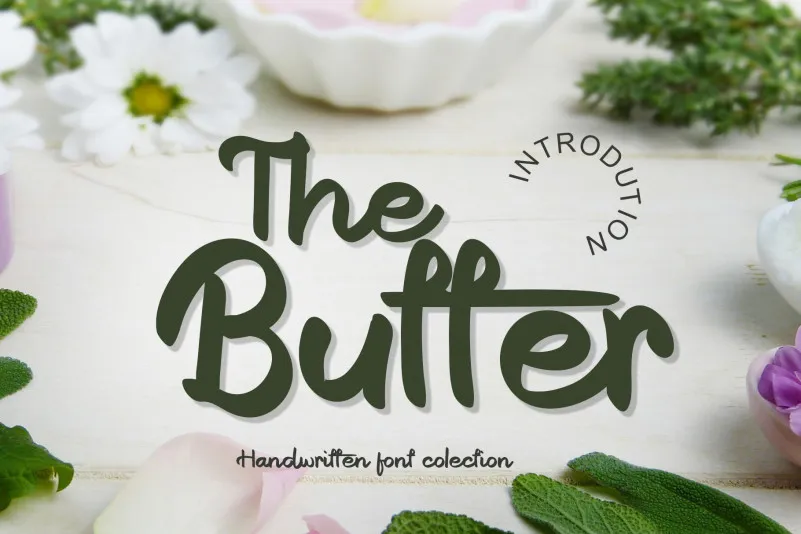
The Butter Script Font – Download Grátis
A fonte “The Butter Script Font” é uma elegante escolha para qualquer projeto que exige estilo sofisticado. Originada dos influentes traços da calligrafia, esta font se mantém atraente e clássica ao mesmo tempo que incorpora um toque de contemporaneidade e frescura. Seu uso versátil faz dela uma excelente opção para diversos propósitos criativos, desde as letras do cabeçalho até o design de materiais de papelaria. Com sua simplicidade elegante e seu charme único, The Butter Script Font é perfeitamente adaptável a um amplo espectro de conceitos e ideias, tornando-a uma fonte indispensável tanto para aquelas pessoas que buscam uma aparência moderna em suas criações quanto para aqueles que desejam um toque nostálgico. Afinal, ela traz o charme da calligrafia clássica de volta às letras e ao design de papelaria contemporâneo.